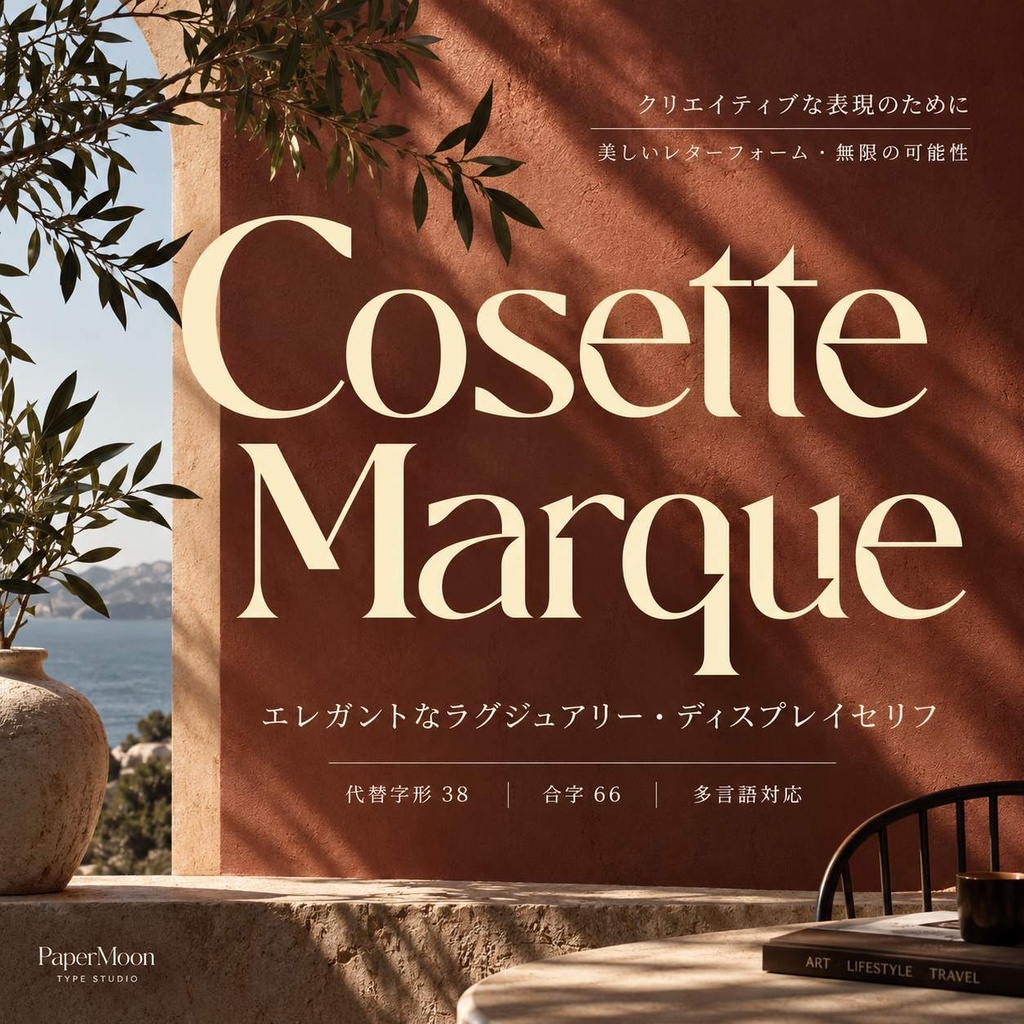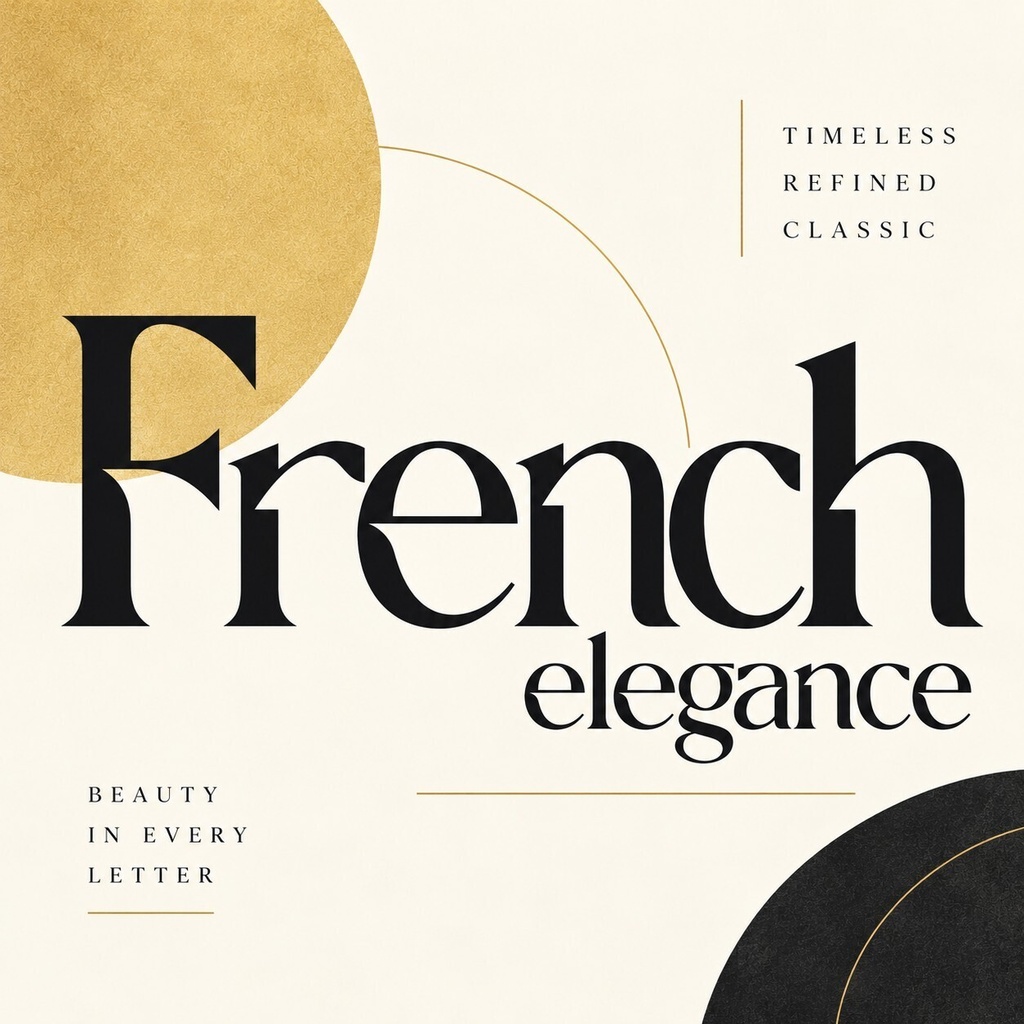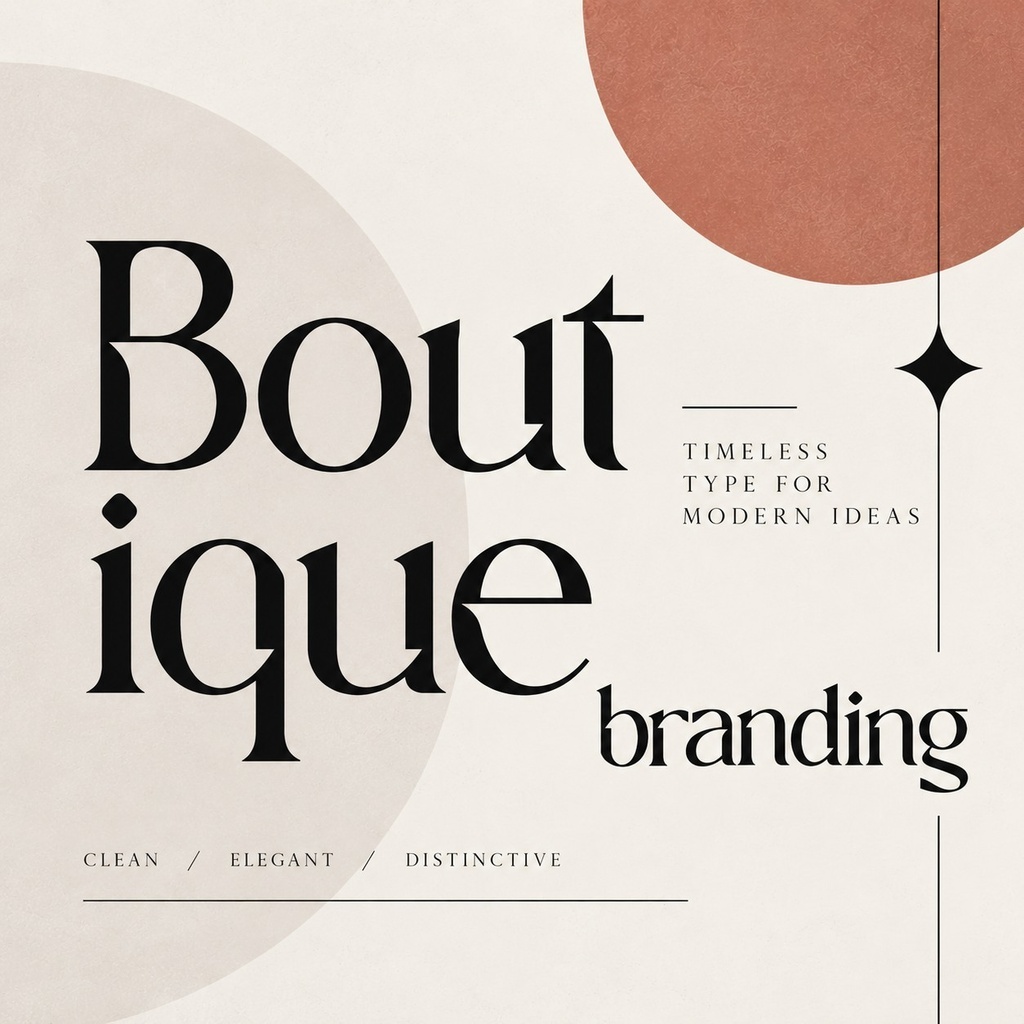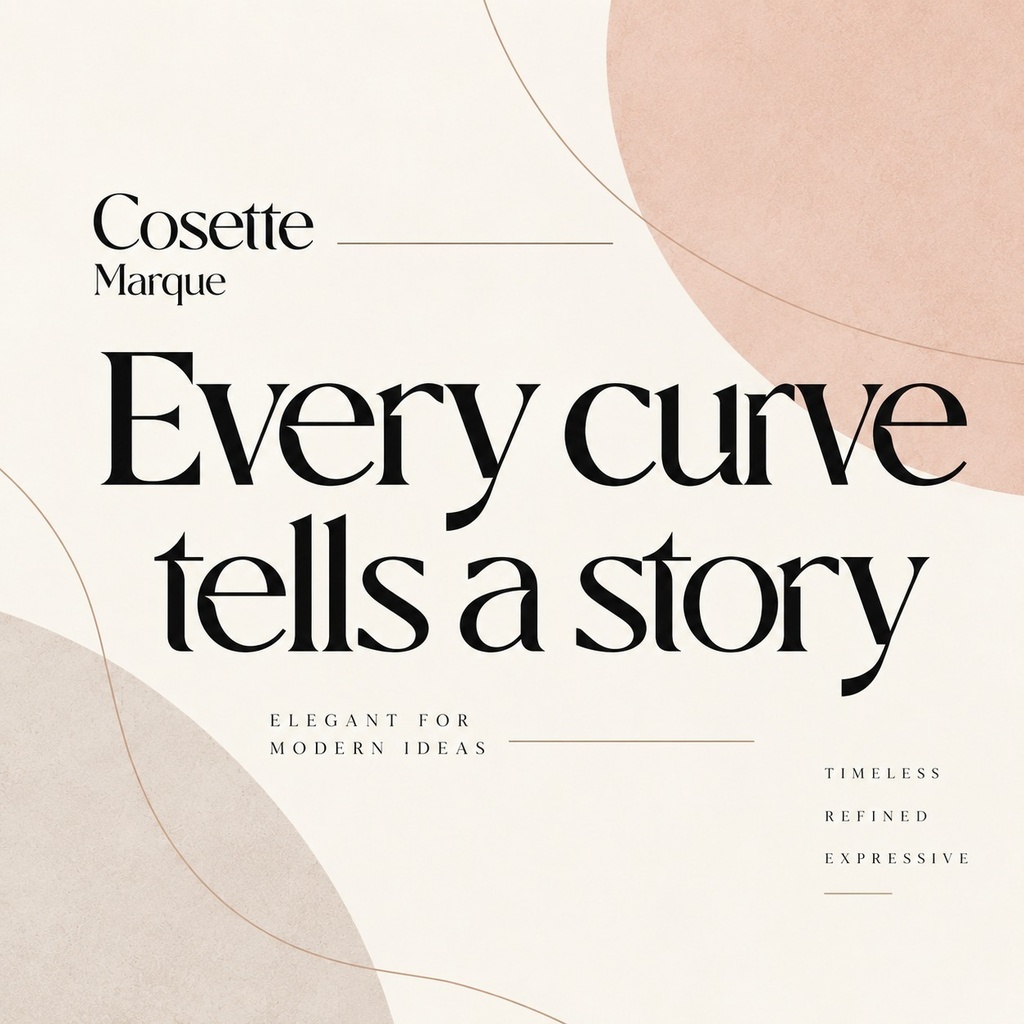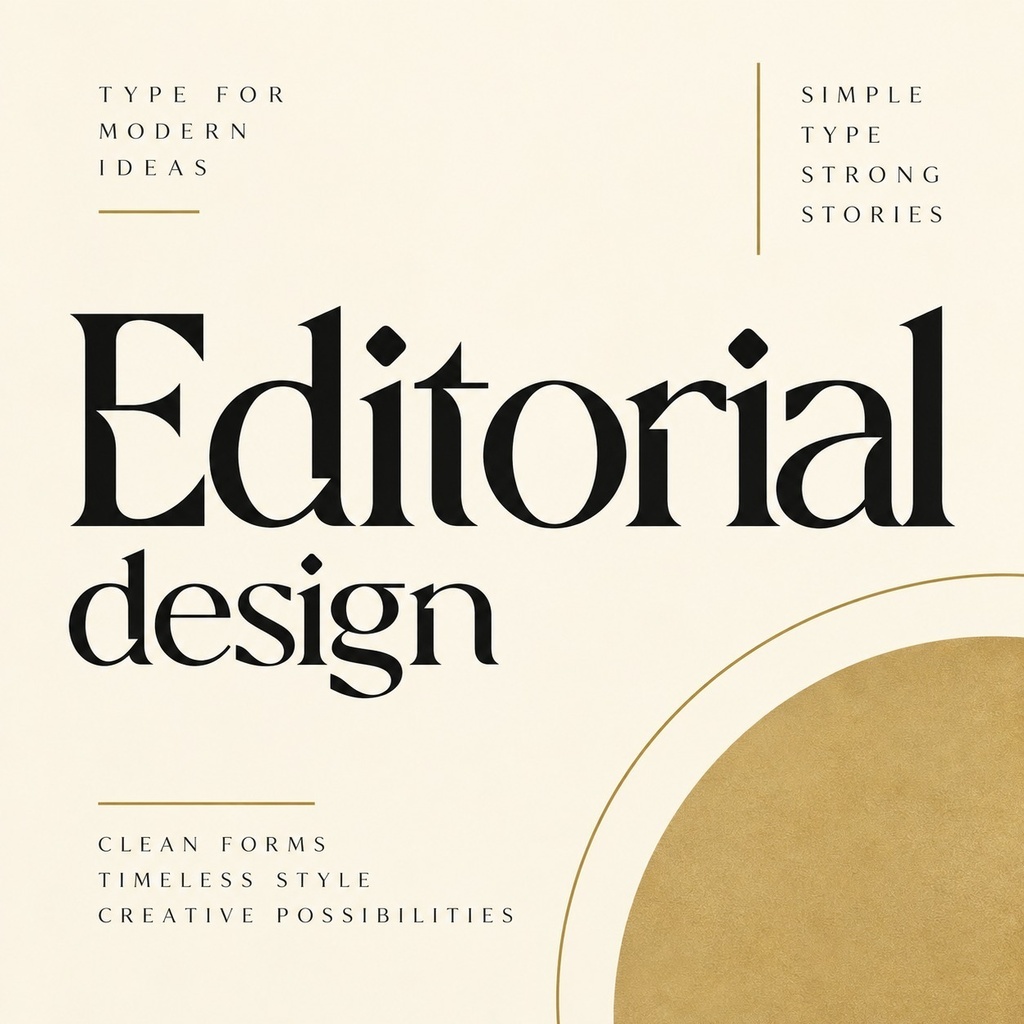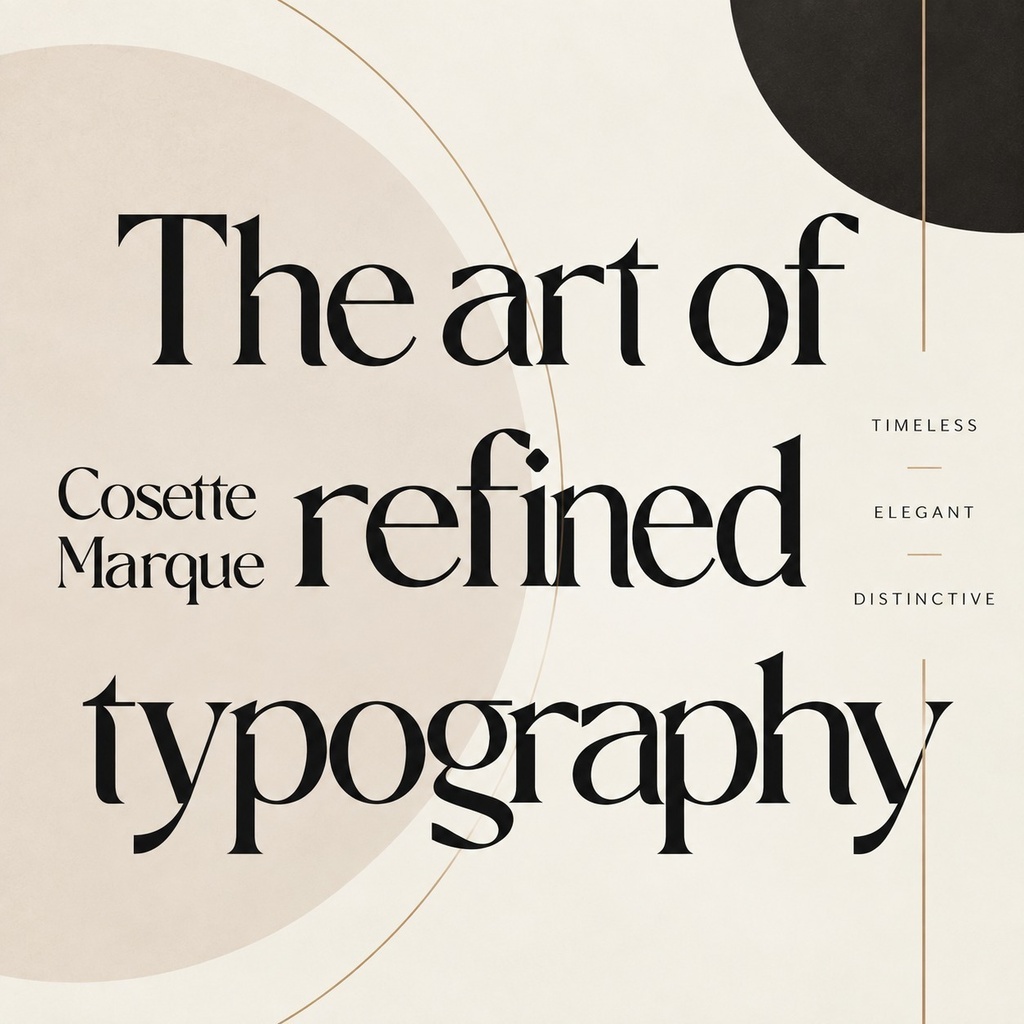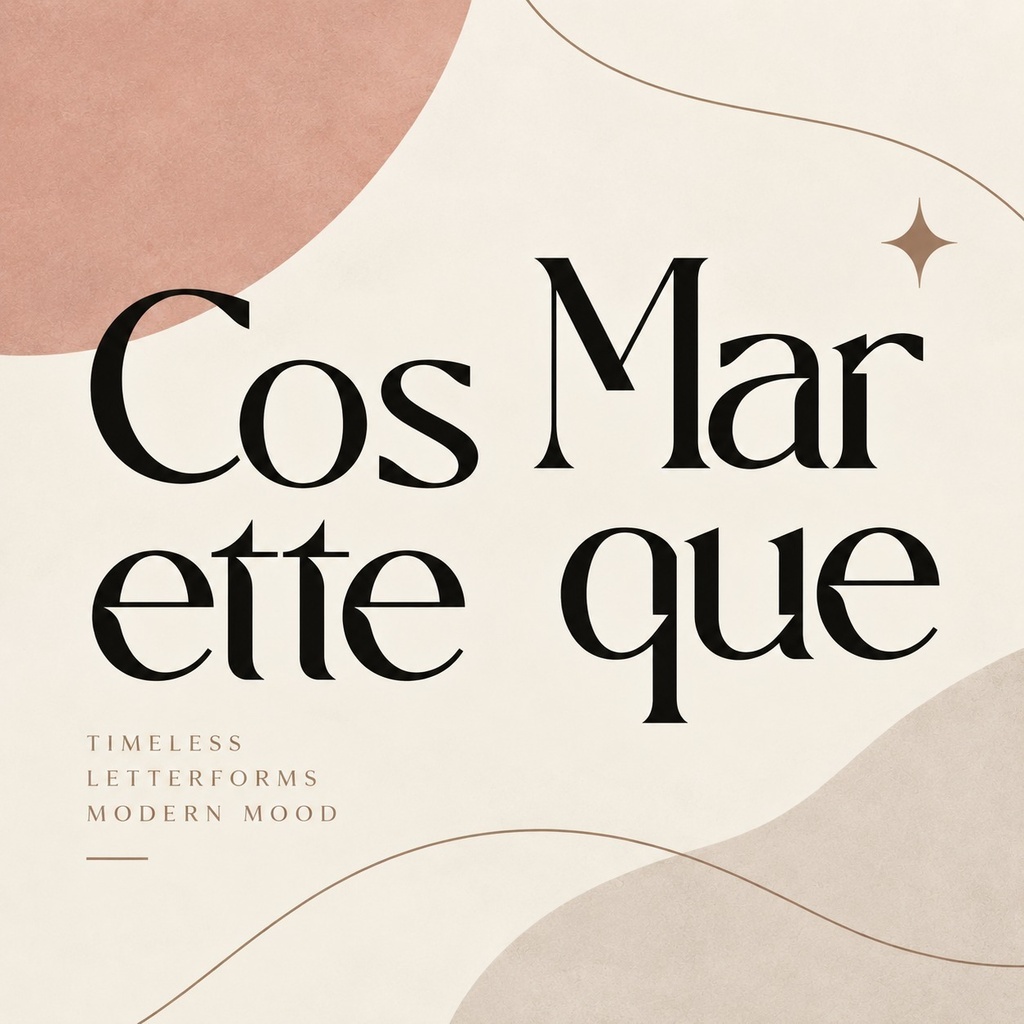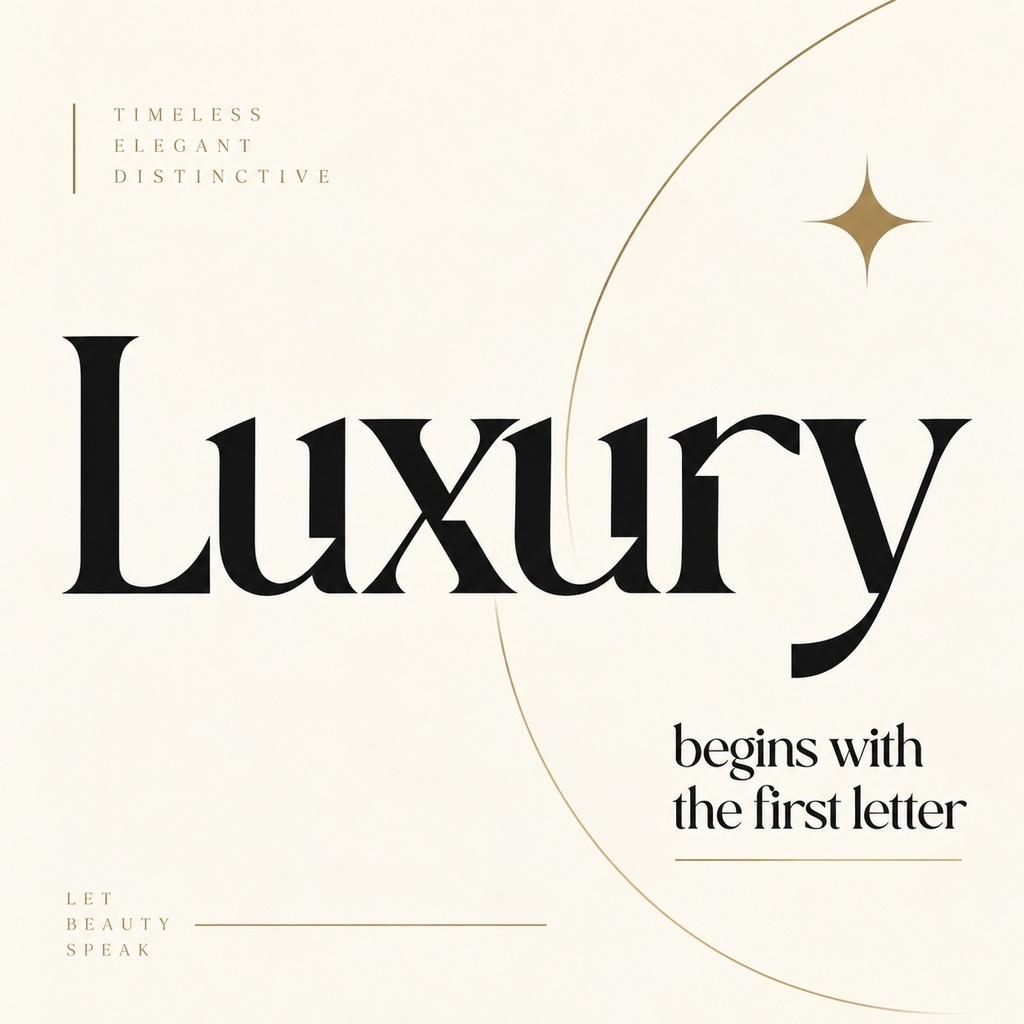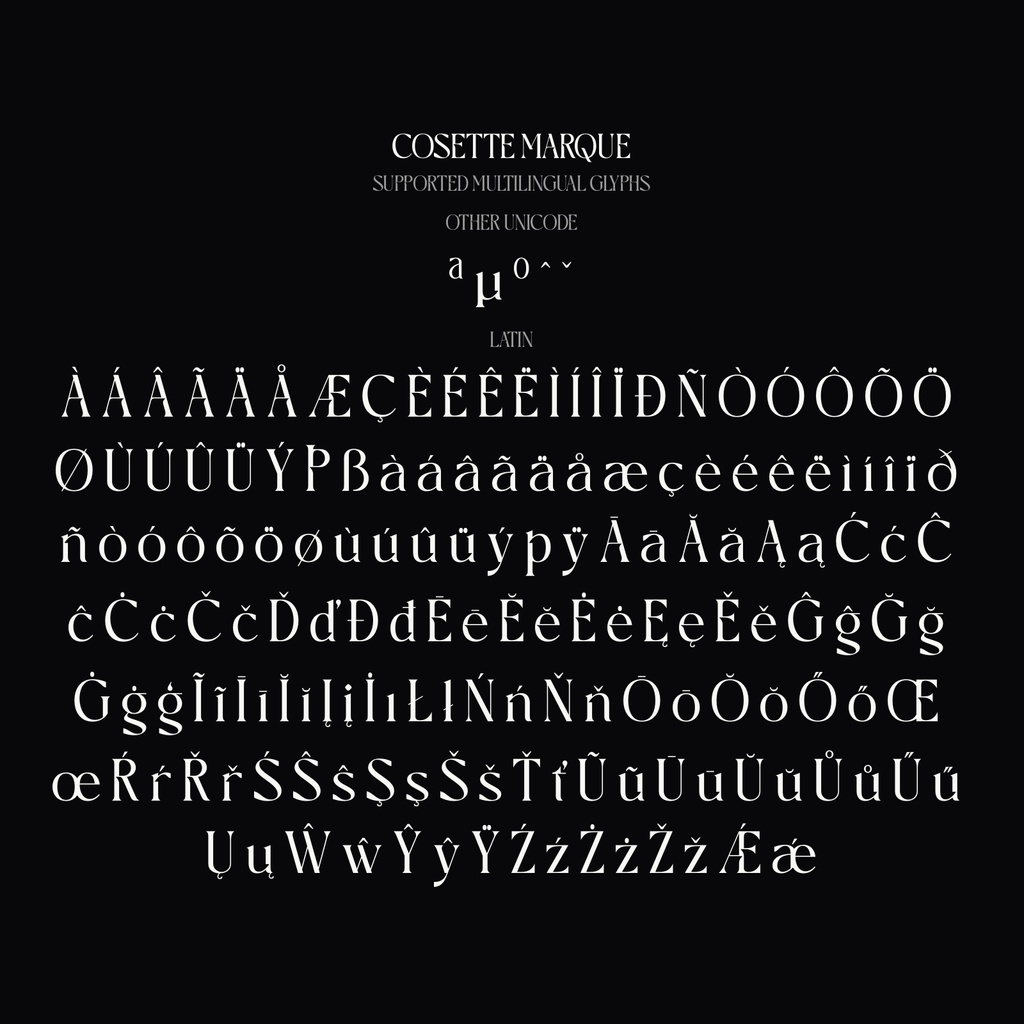
Cosette Marque(コゼット・マルク)【セリフフォント】
高コントラストの華やかなセリフで、ラグジュアリーなロゴやパッケージ、ブランディングを彩るエレガントな歐文フォントです。 Cosette Marque は、高級雑誌のレイアウト、ブティックのロゴ、ファッションキャンペーン、プレミアムパッケージなどにふさわしい、洗練された近代エディトリアルデザインから着想を得たディスプレイ serif です。繊細なフィネスと力強い筆致が調和し、洗練された雰囲気を演出します。 収録内容 フォントファイル: OTF, TTF, WOFF OpenType Feature: 38 Alternates(代替字形)、66 Ligatures(合字) 対応文字: ラテン語基本文字(大文字・小文字・数字・記号)、多言語ラテン語対応 対応文字 ラテン語基本文字(A-Z, a-z, 0-9)と多言語ラテン語文字を収録しています。日本語、キリル文字、ギリシャ文字は含まれていません。 用途 ロゴデザイン、ブランドロゴ、書籍タイトル、雑誌レイアウト、パッケージデザイン、Webバナー、サムネイル、YouTube・テロップ、ウェディング、グッズ、ポスター、同人誌、ゲームタイトルなど。 形式 OTF / TTF / WOFF 対応環境 Windows, macOS 対応。主要なデザインソフトウェア(Adobe Photoshop, Illustrator, InDesign, Figma, Canva 等)で動作します。 利用許諾 Commercial Use(商用利用可): お客様の商業プロジェクト、クライアントワーク、有料販売、ブランド制作、広告、グッズ制作に使用可能です。 Personal Use(個人利用): お客様の個人的な非商業プロジェクト、学習、趣味、プライベートな制作に使用可能です。 フォントの再配布・再販売・埋め込み・テンプレート販売は禁止されています。